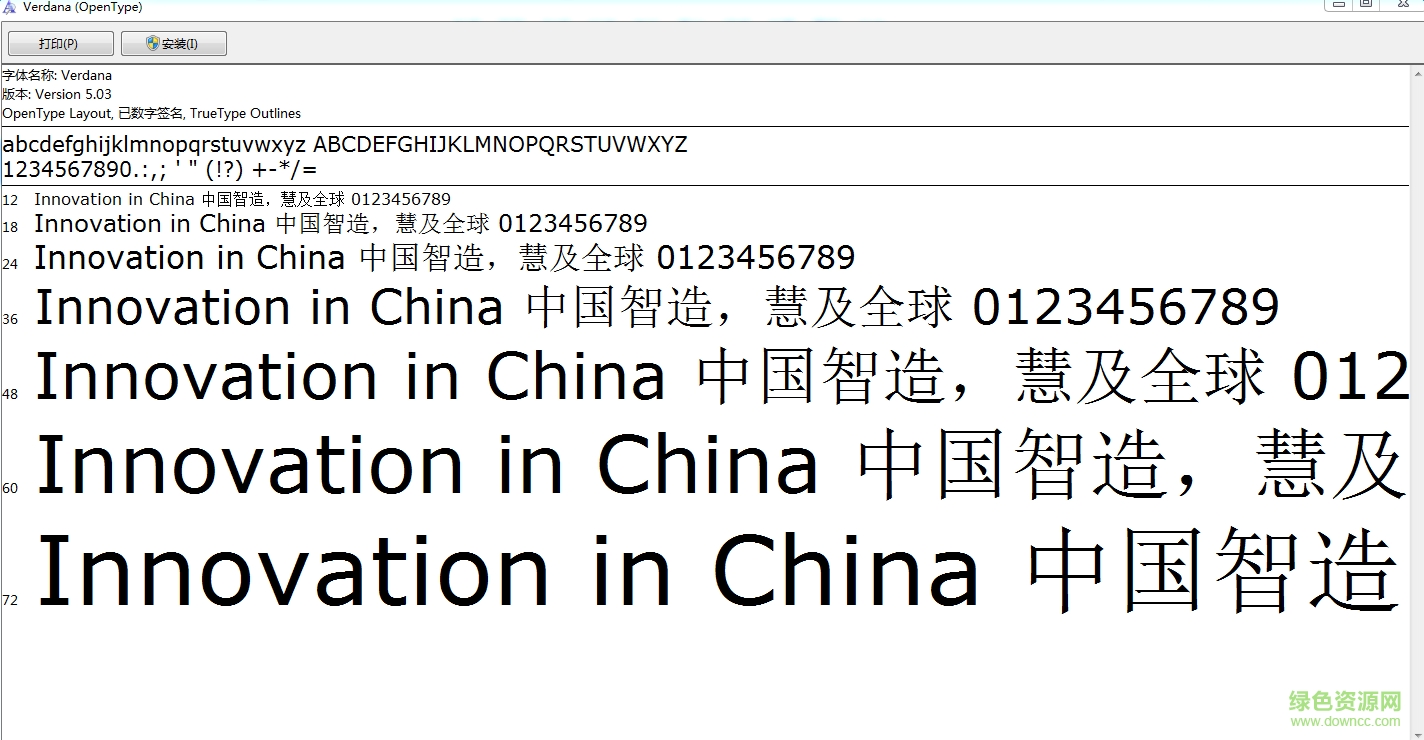
verdana是常見于微軟網(wǎng)頁(yè)的一款核心非襯線體,該字體襯線筆畫自然流暢,字型飽滿,易讀性很高,需要的朋友快來綠色資源網(wǎng)下載吧!
Verdana是一套無襯線字體,它在小字上有結(jié)構(gòu)清晰端整、閱讀辨識(shí)容易等高品質(zhì)表現(xiàn),成為許多領(lǐng)域愛用的標(biāo)準(zhǔn)字型之一。此字體設(shè)計(jì)源起于微軟字型設(shè)計(jì)小組的維吉尼亞·惠烈(Virginia Howlett)希望設(shè)計(jì)一套具有高辨識(shí)性、易讀性的新字型以供屏幕顯示之用,于是她邀請(qǐng)了世界頂級(jí)字型設(shè)計(jì)師之一的馬修·卡特(Matthew Carter)操刀,以Frutiger字體及愛德華·約翰斯頓(Edward Johnston)為倫敦地鐵所設(shè)計(jì)的字體為藍(lán)本,并由Monotype公司的字型微調(diào)專家湯姆·瑞克納(Tom Rickner)擔(dān)任手工微調(diào)